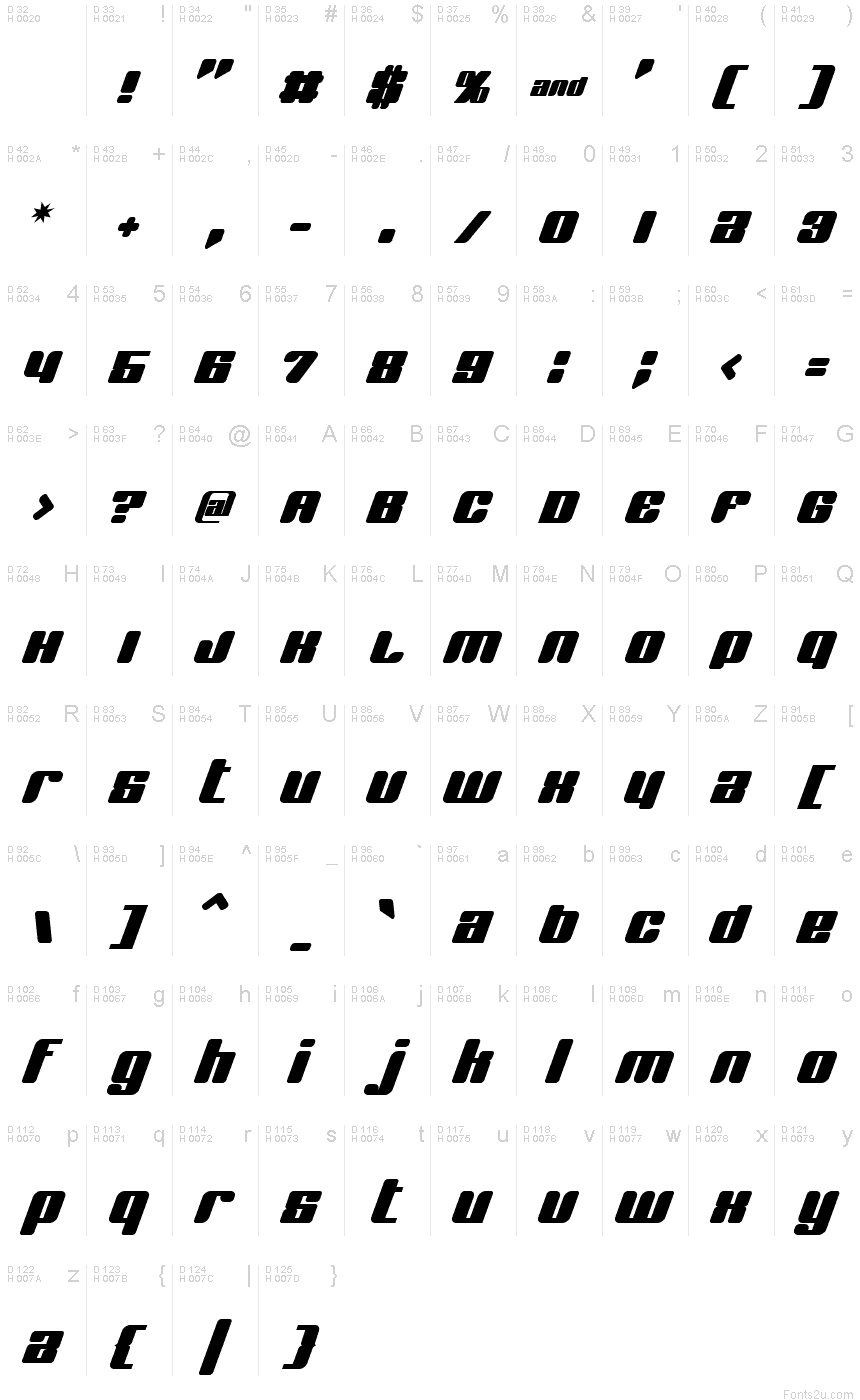
BN Jinx autorstwa Bena Nathana to bezpłatny retro krój pisma typu display z szybkim, skośnym wykończeniem, które sprawia wrażenie, jakby było w ciągłym ruchu. Litery są masywne i ciasno osadzone, z ostrymi wcięciami i wyrazistymi kątami, które przywodzą na myśl naklejki z wyścigówek – są nasycone, śmiałe i nieco zadziorne.
Używając BN Jinx, nadasz natychmiastowego charakteru logotypom, tytułom na plakatach, okładkom albumów, ulotkom w stylu arcade, grafikom skate lub streetwear, opakowaniom produktów oraz nagłówkom w mediach społecznościowych. Stosuj go w dużym rozmiarze, aby zachować wyrazistość ciasnych kształtów, a w tekście głównym łącz z neutralnym, spokojnym bezszeryfowym krojem (jak czysty grotesk) – ten darmowy font stworzono po to, by krzyczał.